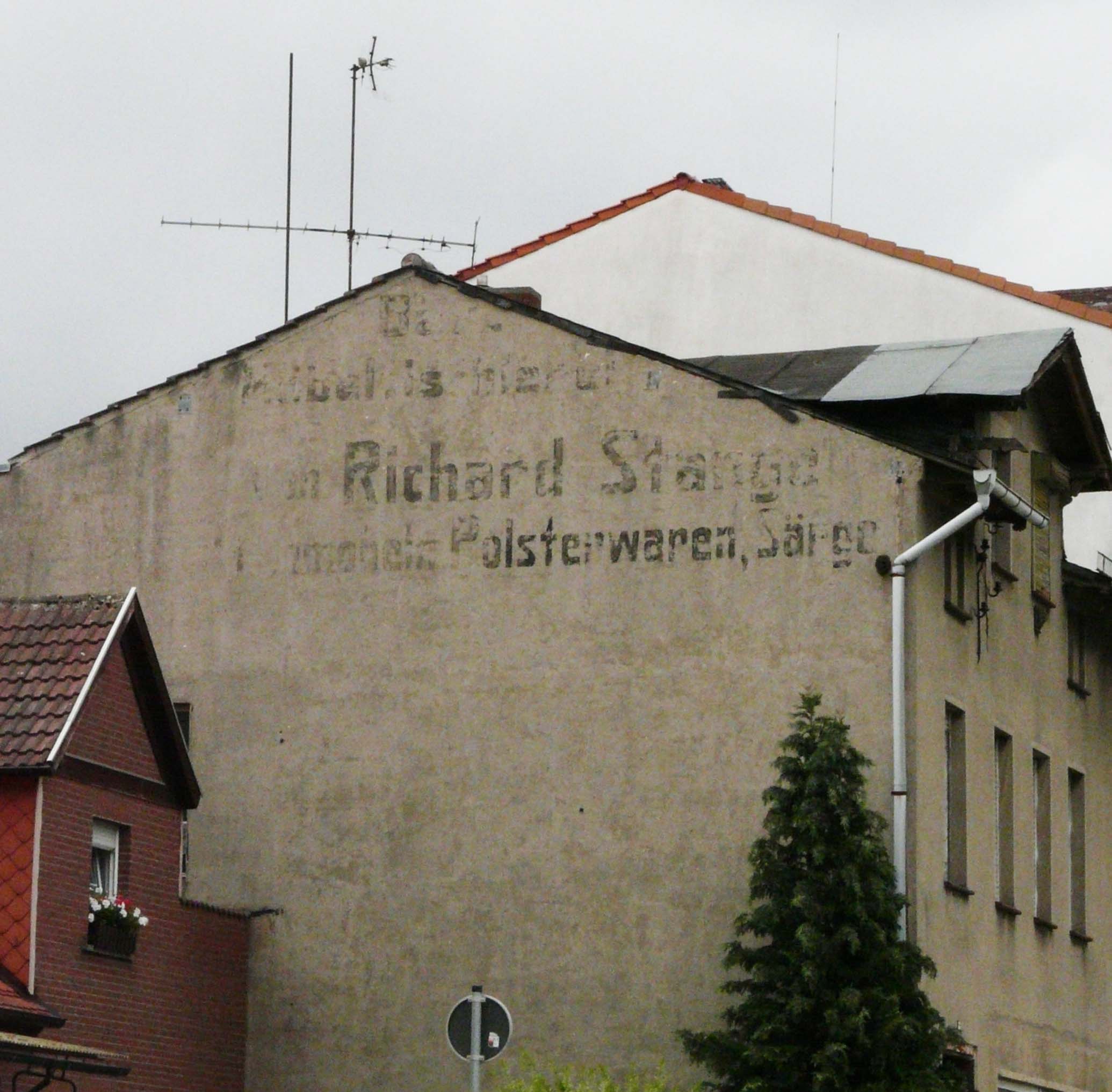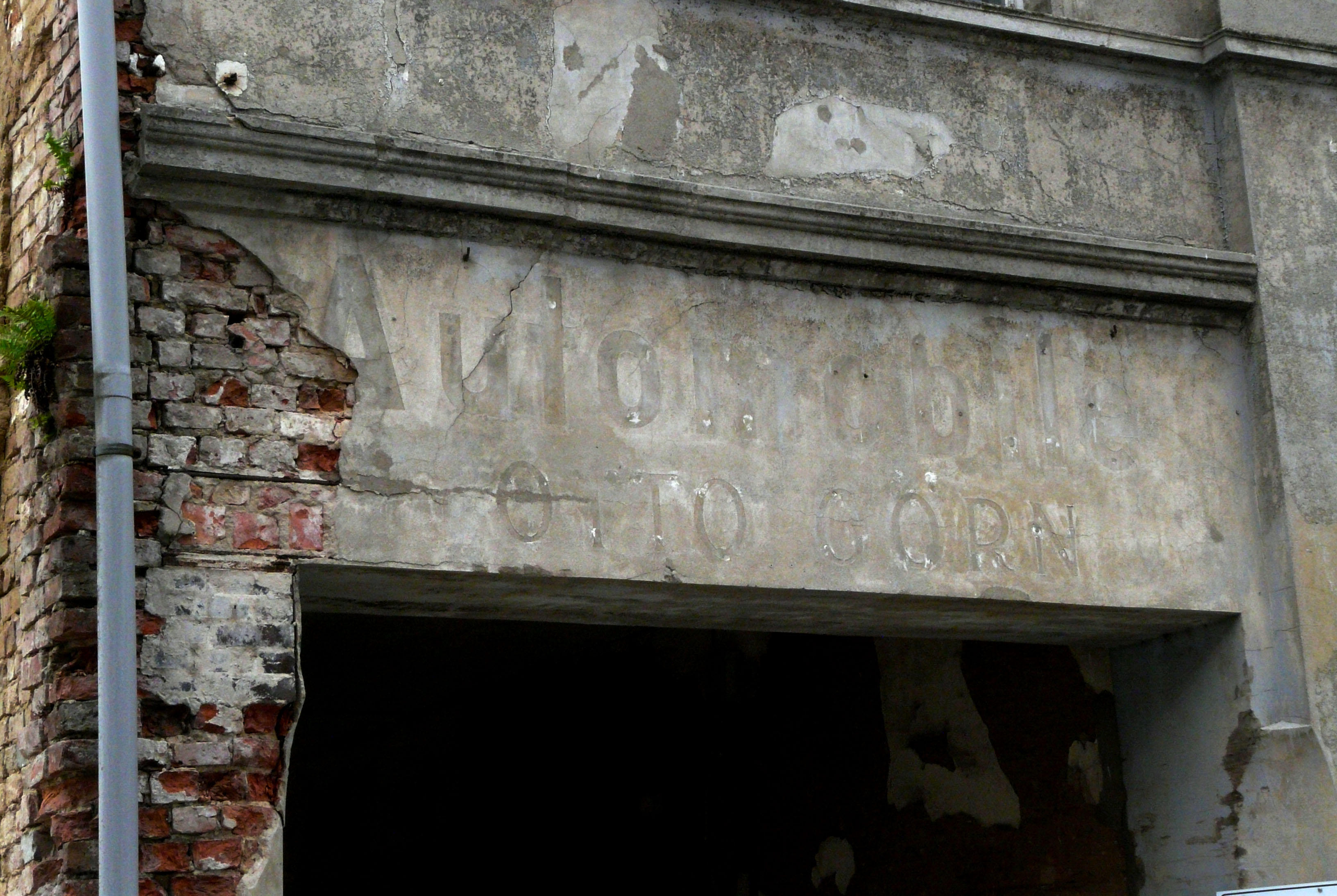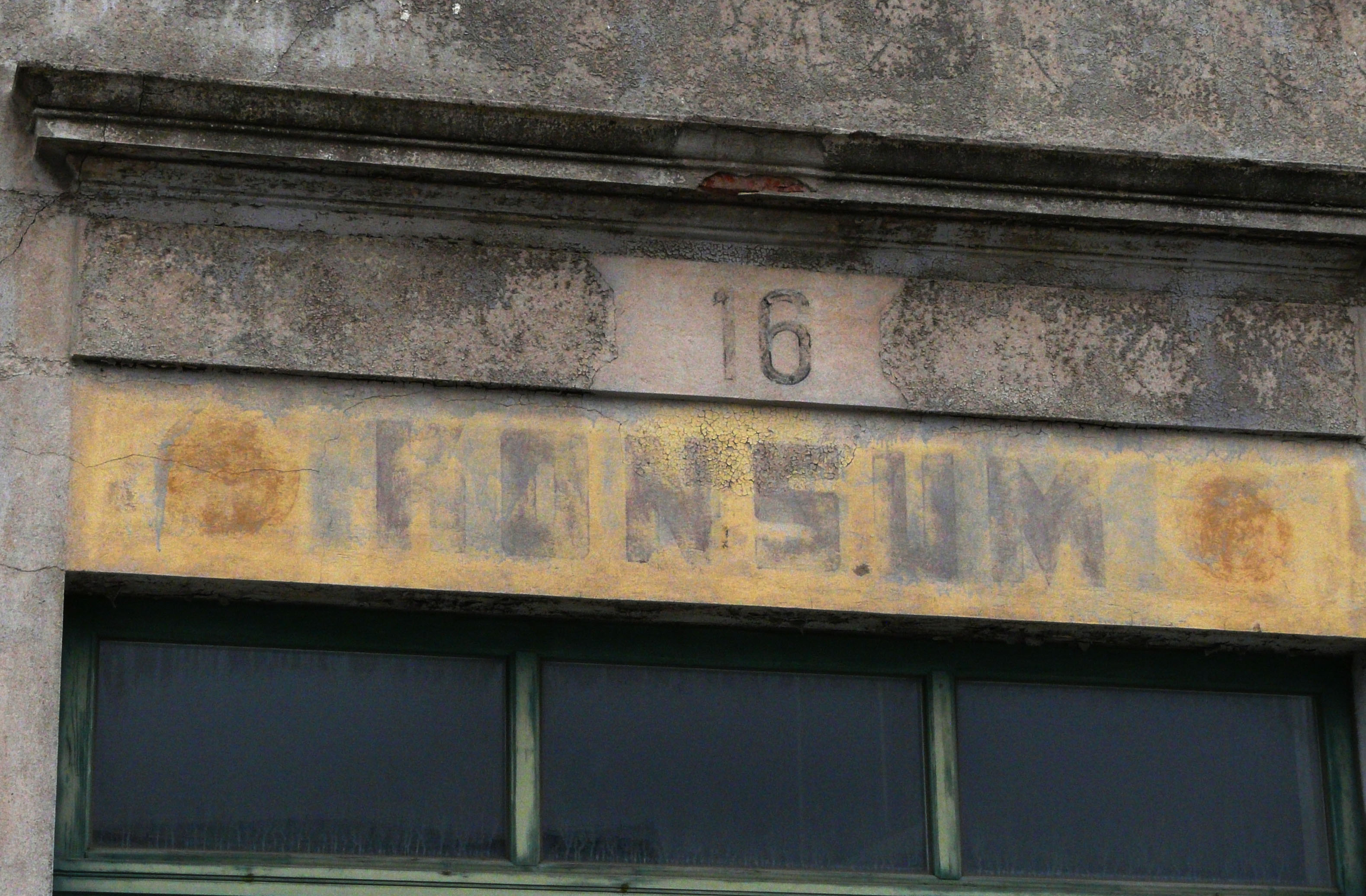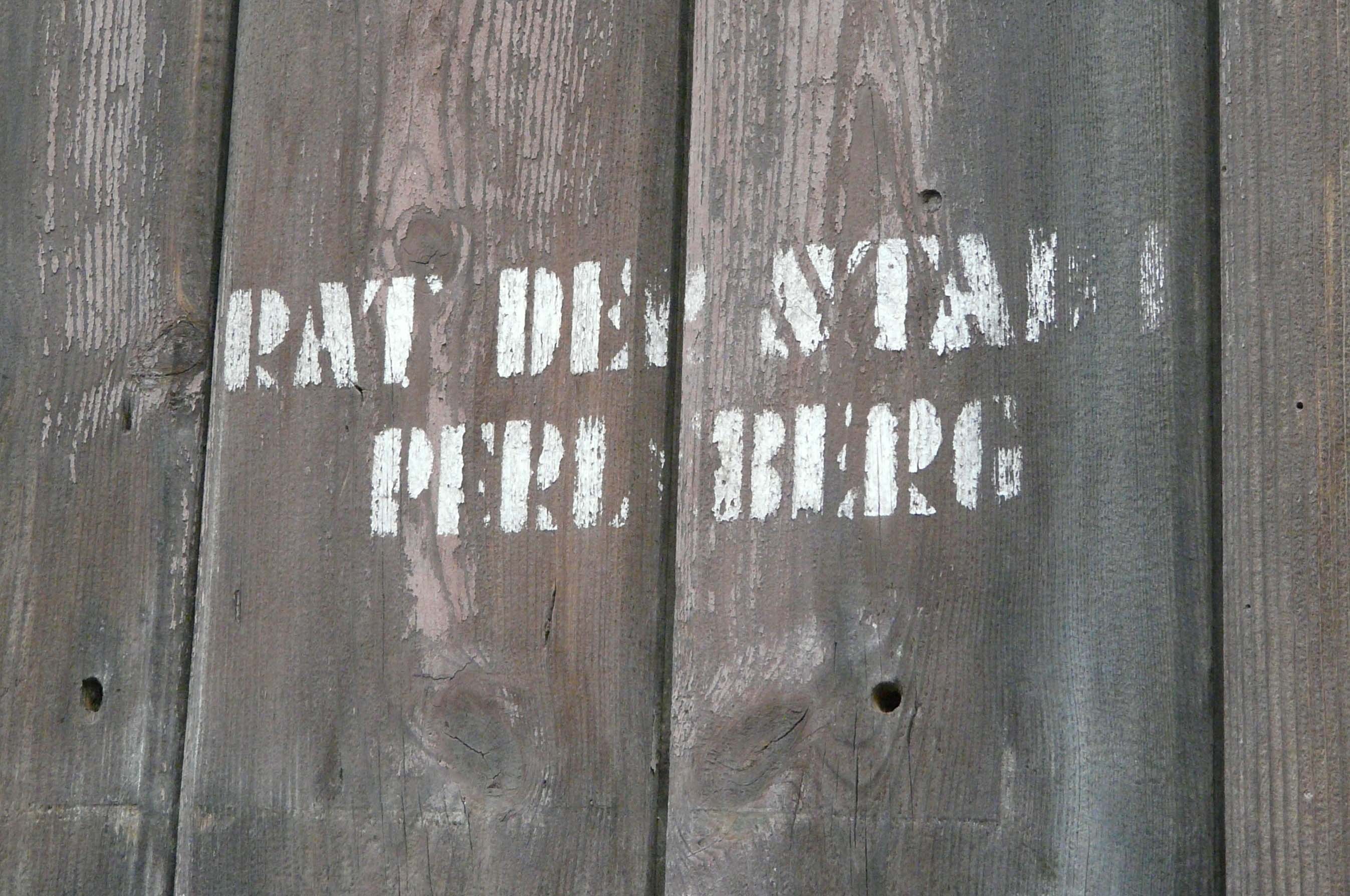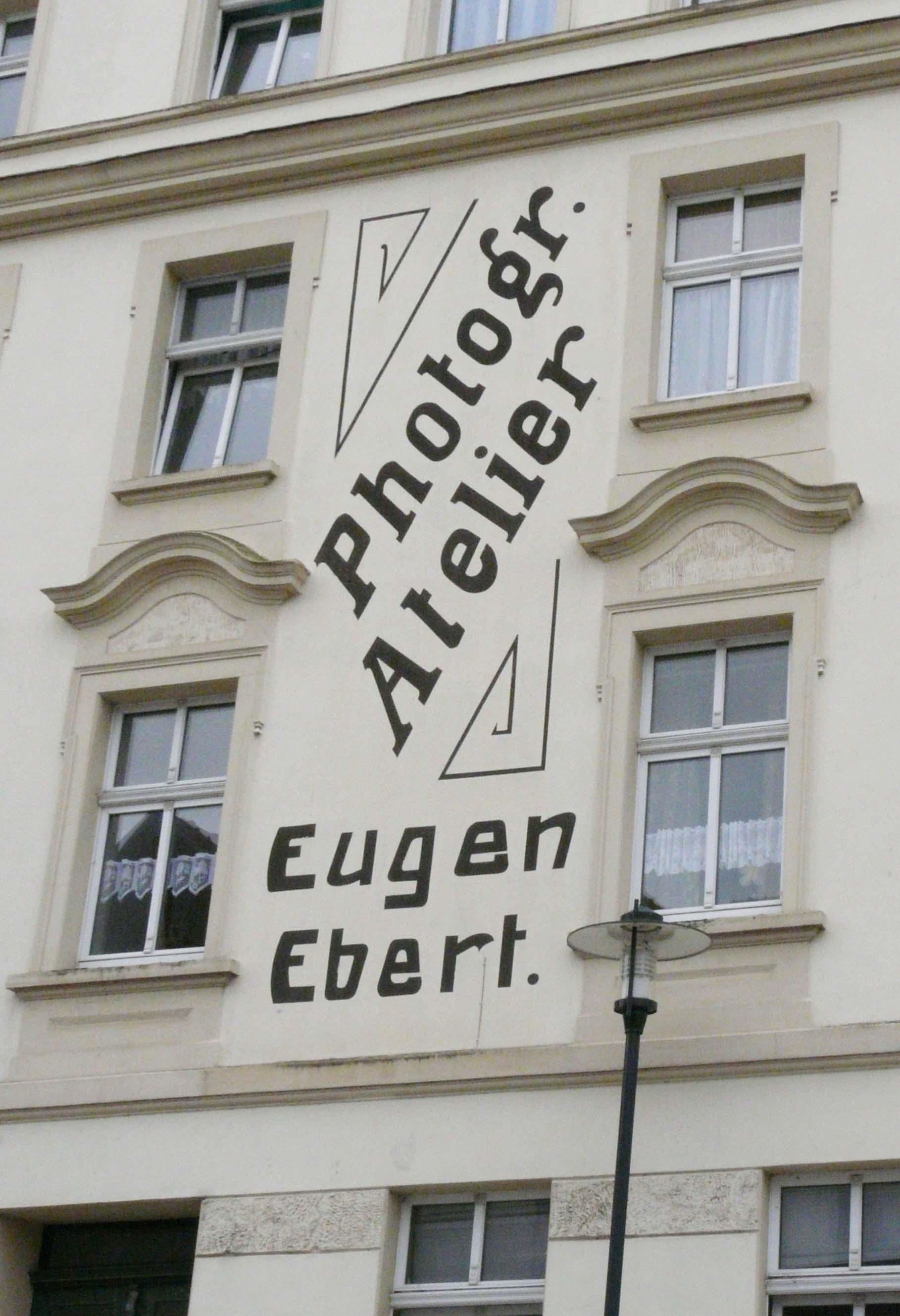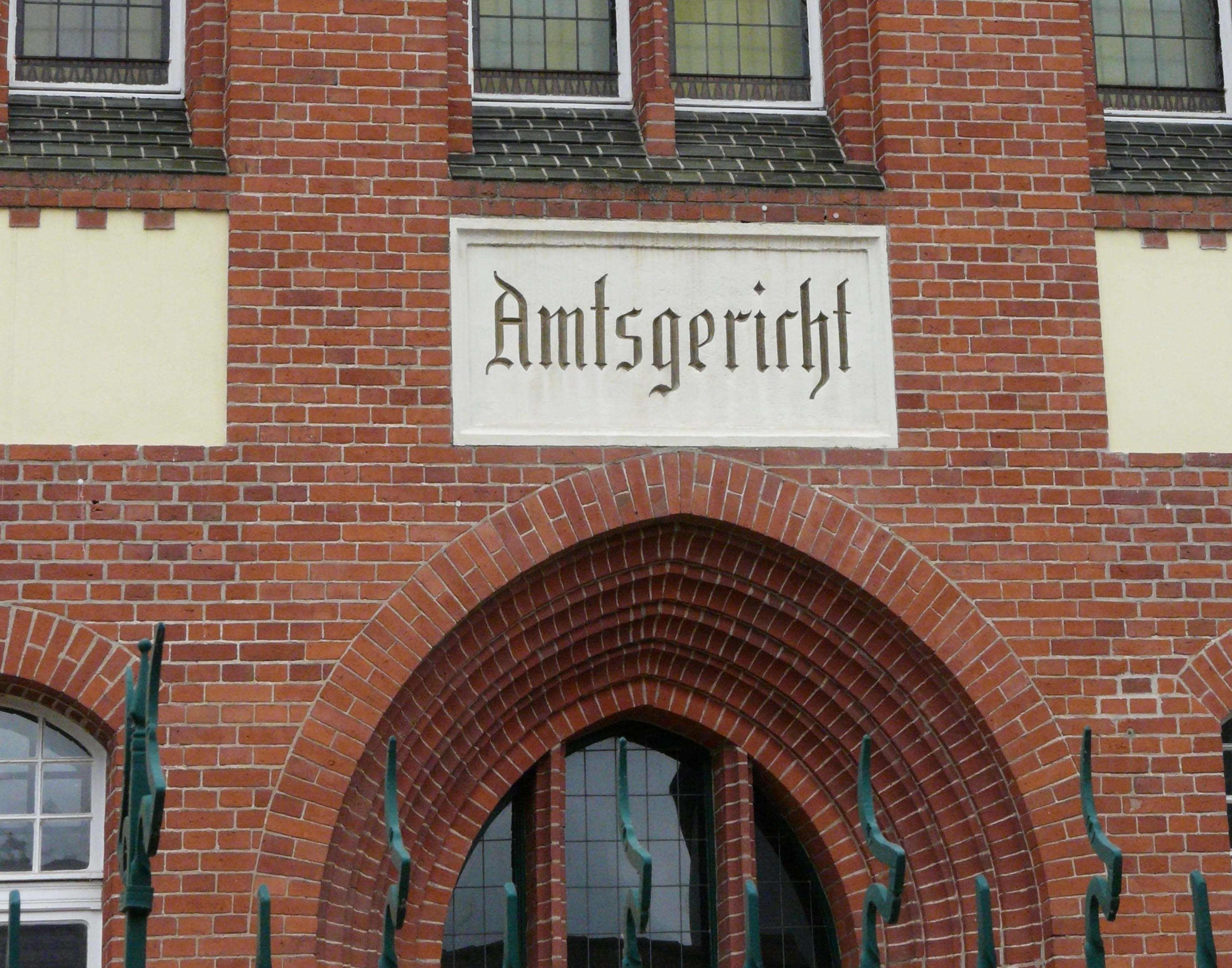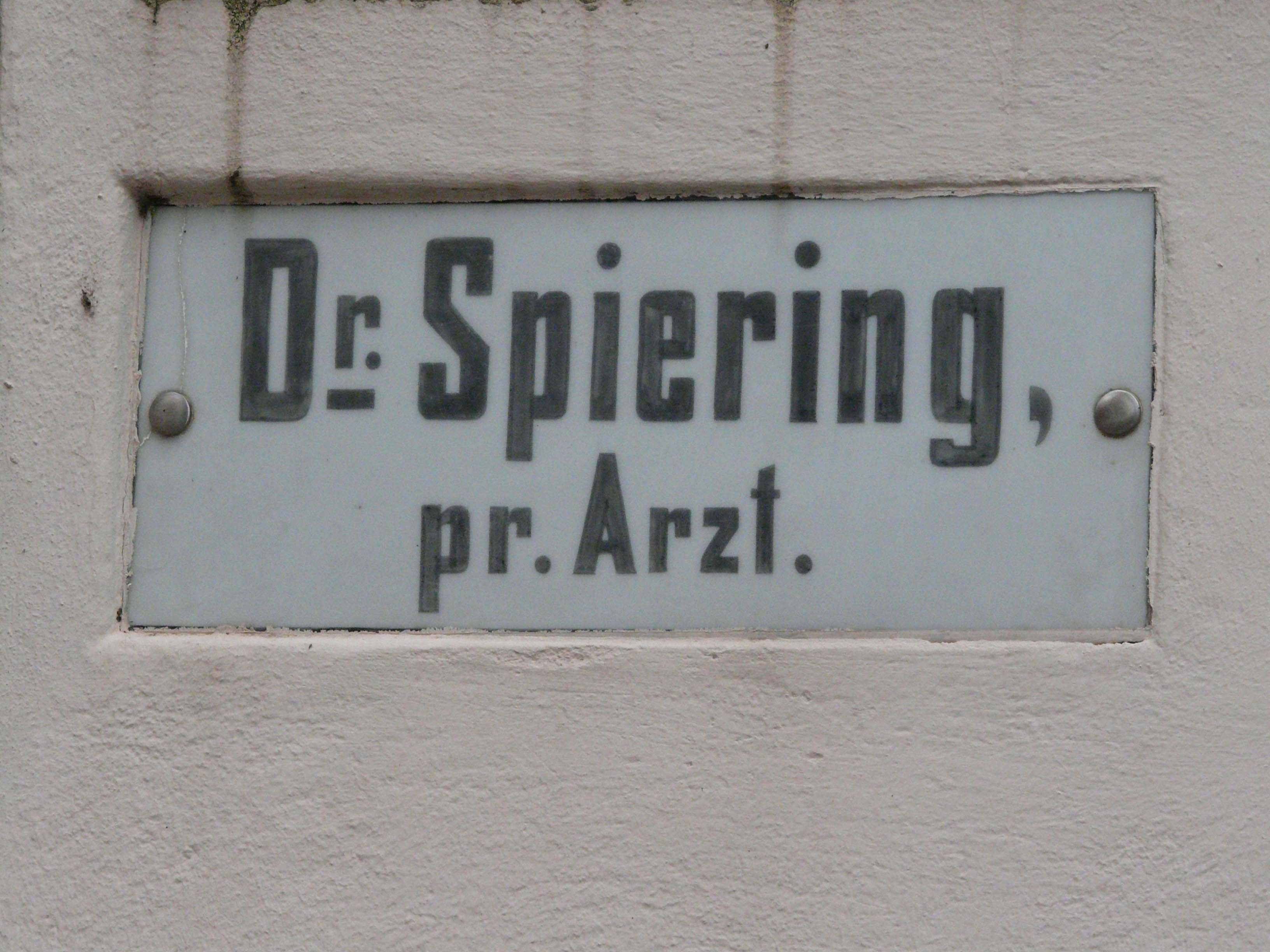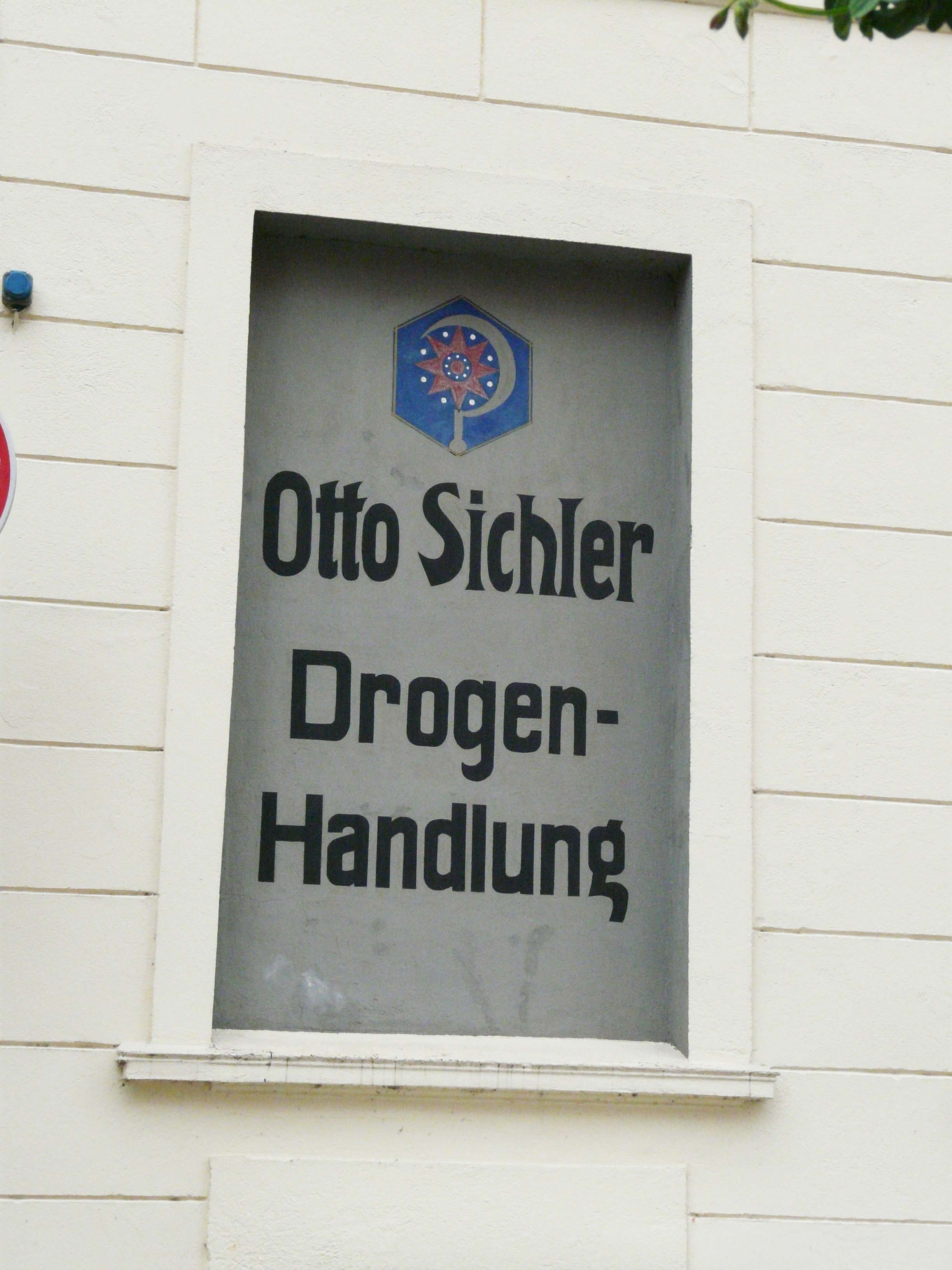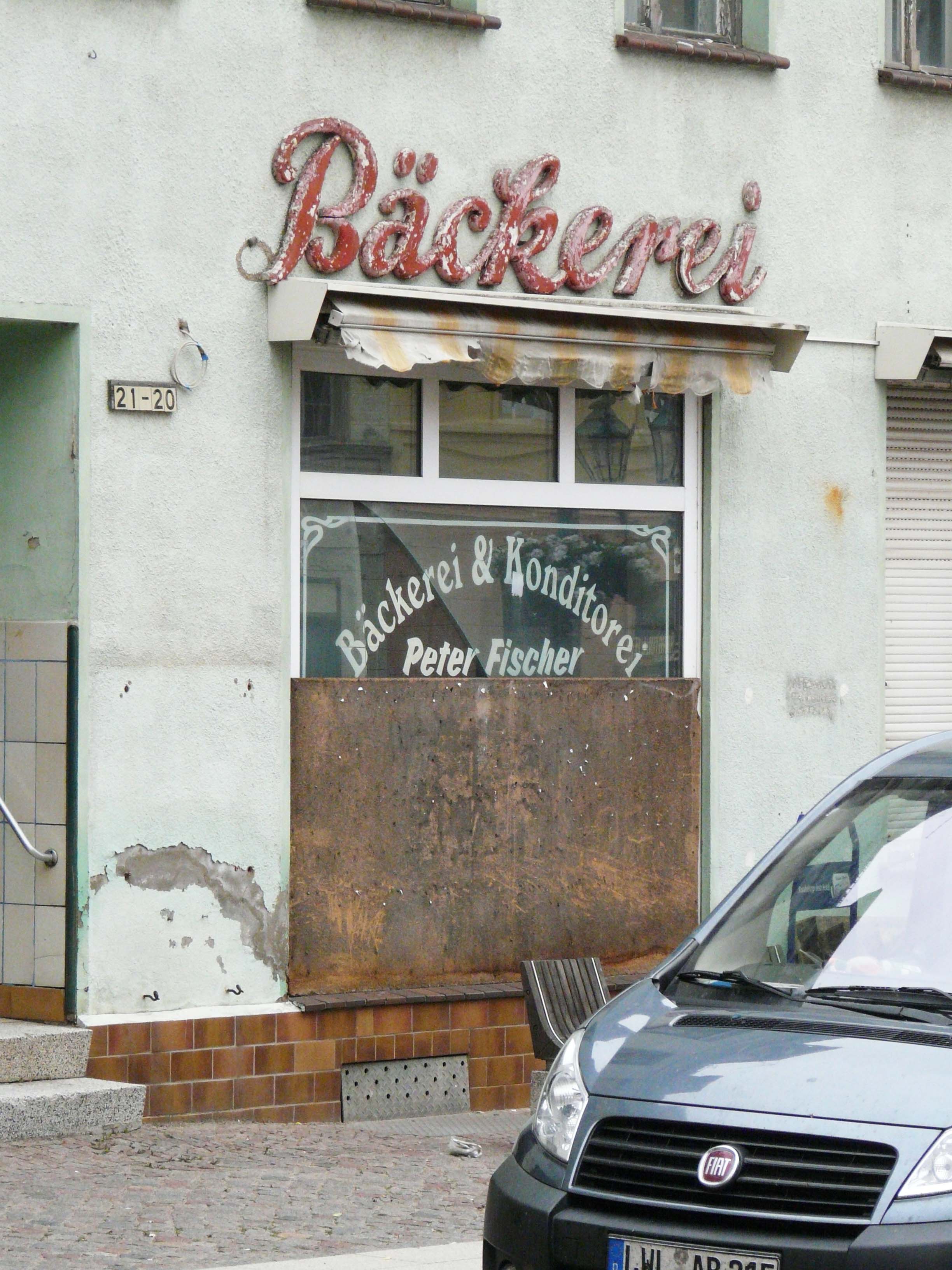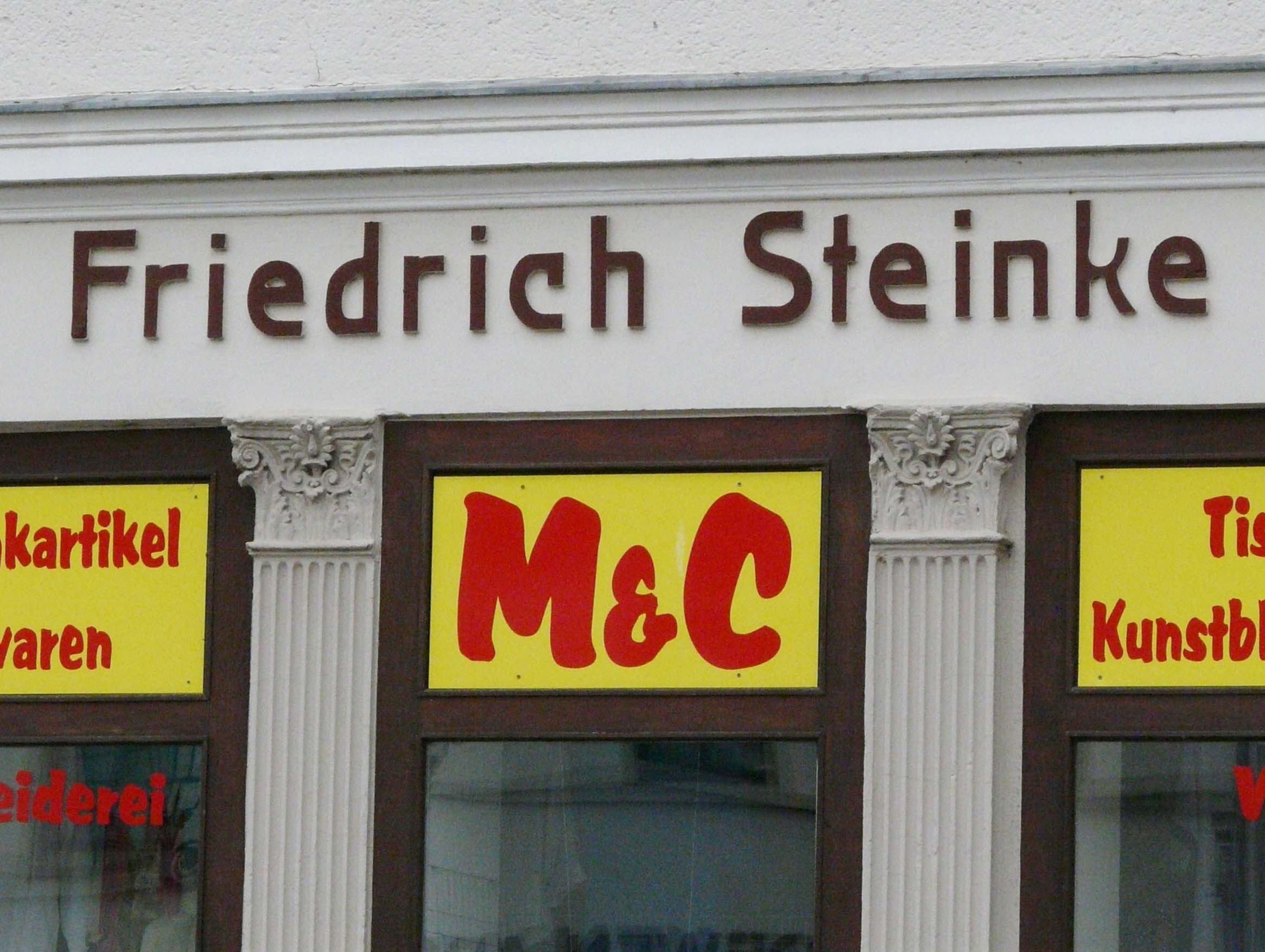
Typostreifzug durch die Stadt ...
Was ist denn das für ein tolles Fundstück? Das schaut so aus, als hätte jemand auf der grünen Wiese diese (ehemalige) Fassadenbeschriftung montiert und ausgestellt. Gab es dort noch andere vergleichbare Ausstellungsstücke? Oder kannst du evtl. etwas zum Präsentationsort sagen?
Das ist "Kunst am Radweg" bei Wanfried an der Werra.
Also dieses Fundstück habe ich mitten in Eschwege fotografiert, direkt an der Werra in der Nähe des Schwanenteichs. Es kann allerdings gut sein, dass es in Wanfried ein weiteres Exemplar gibt, das ist mir aber nicht aus persönlicher Anschauung bekannt.  :-D
Heute das Kloster Plankstetten besucht … momentan wird es saniert und renoviert, die EU, der Staat und der Freistaat Bayern pumpen da ordentlich Geld hinein. Fassadendämmung, komplette Neugestaltung der Fassade und so weiter. Auch innen tut sich einiges: beispielsweise sind die Toilettenanlage neu – in einer Qualität, dass jeder private Bauherr Pleite wäre. Die Trennwände aus furnierter Eiche, geölt, alle Fliesen nur vom Feinsten … mein Schwager, Berufsschullehrer für Bauwesen, hat mich ein wenig aufgeklärt, was das alle kosten mag.
Nicht zuletzt, und das finde ich aber einfach toll, wird die Beschilderung nicht einfach beim Folienschnitz bestellt, sondern von ruhiger Hand direkt auf die weißen Wände aufgemalt. Ich hab für euch ein paar Bildchen gemacht …
Bleibt zu hoffen, dass der Künstler die zukünftige Beschilderung  besser hinbekommt.
Besten Dank. Leider nicht ganz das, was ich mir in meiner Fantasie zusammengereimt hatte.
Das stimmt natürlich – Deine Vermutung war charmanter!  :nicken:
Für mich sieht das so aus, als wäre es in einem Rutsch durchgeschrieben. Die t-Striche ähneln sich alle sehr und sind mit dem gleichen Stift geschrieben. Ich habe das eigentlich eher als Scherz aufgefasst – so nach dem Motto »Reim’ Dich oder ich fress’ Dich«.  ;-)
Bei dem »Rauchen verboten«-Schild aus Altona hat offensichtlich die Bradley
bzw. einer ihrer Nachahmungen Pate gestanden. Eine sehr interessante Variation.
Kathrins 19 d – mit dem Stöpsel, den man umstecken kann – genial!